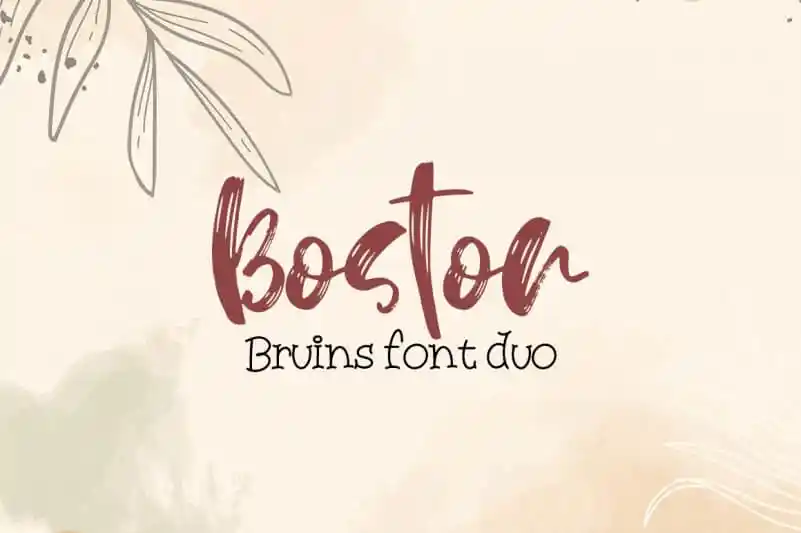
Boston Bruins font duo – Download Grátis
A Boston Bruins Font Duo é uma inovação na categoria de fontes de script, criada pelo designer Alexander. Esta elegante fonte de calligrafia apresenta um estilo moderno e sofisticado, perfeita para criações gráficas que buscam ser elegantes e únicas. Com suas linhas fluidas e detalhes refinados, a Boston Bruins Font Duo pode ser usada em diversas formas, desde nomes de marca até selos corporativos e até mesmo em artigos de moda. Seja você um designer de logotipo ou criador de materiais de merchandising, essa fonte oferece uma maneira original de expressar sua identidade visual. Com a Boston Bruins Font Duo, é simplesmente fazer seu design soar excepcional.